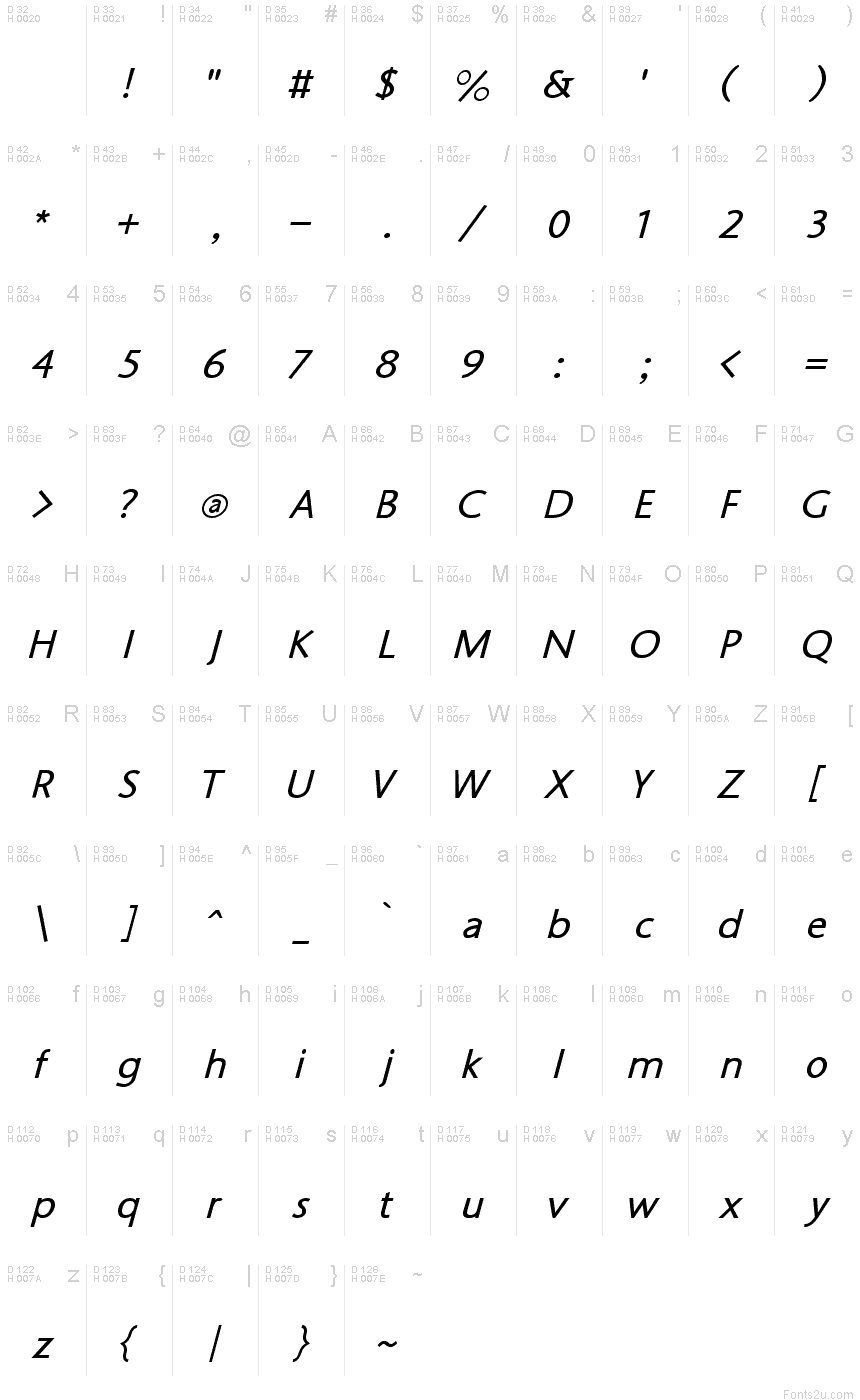
Oski Dakelh Italic od Chrise Harveyho je bezplatné humanistické bezpatkové písmo s rychlým, ručně psaným sklonem a jemným nádechem rané digitální éry. Písmena jsou hladká a lehce elastická, kombinují široké oválné křivky s ostrými spoji a vysoký, zametavý rytmus, který fontu dodává lehký, konverzační tón.
Díky tomu je tento bezplatný font přirozenou volbou pro kulturní plakáty, vzdělávací materiály, muzejní grafiku, obálky knih a webová záhlaví, kde by obyčejné bezpatkové písmo působilo příliš neutrálně. Dobře funguje také v krátkých titulcích, citacích a prvcích vizuální identity, protože kurzíva dodává i jednoduchým slovům pocit pohybu, aniž by působila příliš zdobně.